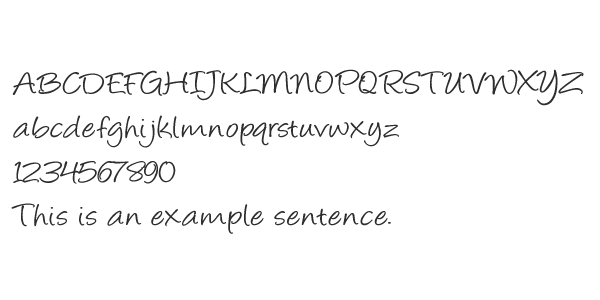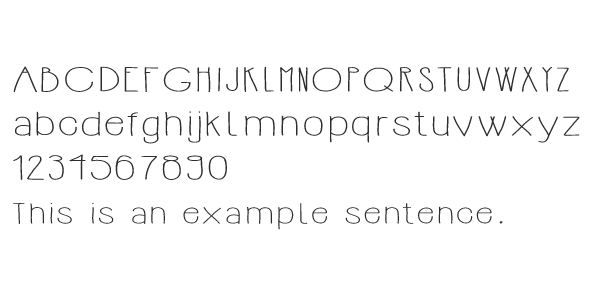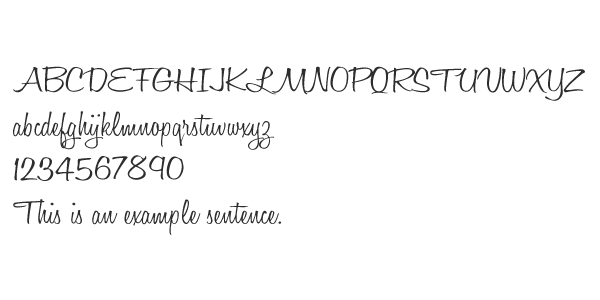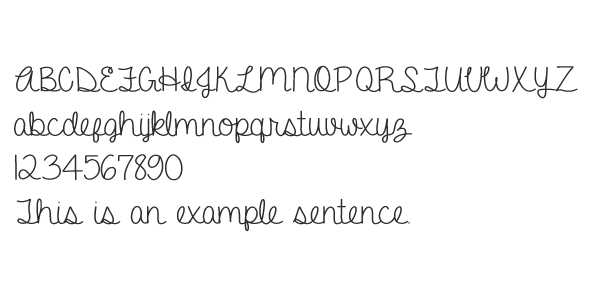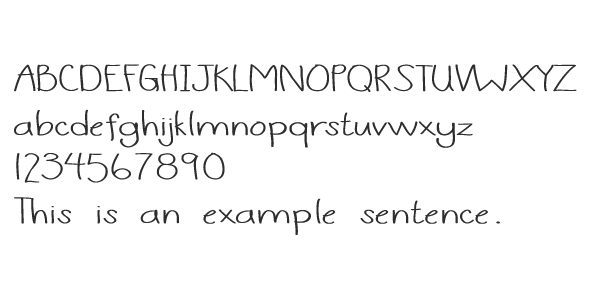
Wie kann man handgeschriebene Schriftarten weiter klassifizieren?
Ich befasse mich gerade mit dem Thema 'handwritten fonts".
Wie könnte man folgende Schriftarten voneinenader abgrenzen bzw. nochmals eigens benennen (alle gehören ja unter den großen Deckmanten "handwritten/handdrawn fonts"):
Es gibt verbundene und nicht verbundene Handschriften. »Normale« und kalligrafisch inspirierte Handschriften. Man kann Handschriften in begrenztem Maße nach Herkunft einordnen, da einige Buchstaben im Laufe der Zeit regional unterschiedlich ausgeformt wurden (siehe beispielsweise E/e in englischen Schreibschriften). Es gibt Handschriften, die die gedruckten Buchstaben nachahmen, und im Volksmund »Druckschrift« genannt werden und Handschriften in reinen Versalbuchstaben, die als »Blockschrift« bezeichnet werden.
Von oben nach unten:
Schreibschrift (verbunden!) oder Schulschrift* – wahrscheinlich nordamerikanisch (?)
Die nächsten drei würde ich eigentlich gleich einordnen zu den handgeschriebenen (handwritten) Antiquaschriften.
Das letzte wäre eine Pinselschrift – brush script
* Zu dem Thema habe ich mal einen interessanten Vortrag im Museum der Arbeit gehört – ich glaube das gehörte sogar zur Diplomprüfung: http://florian.hardwig.com/manuscribe/FHardwig-PAGE-2007-07.pdf
Da wurde sehr deutlich gezeigt, wie und wo die Unterschiede in den in einzelnen Ländern sind.